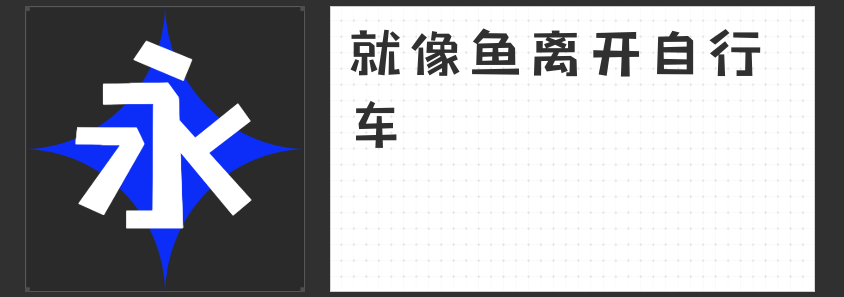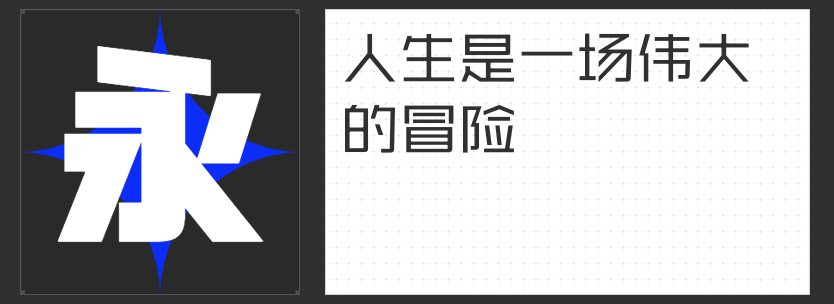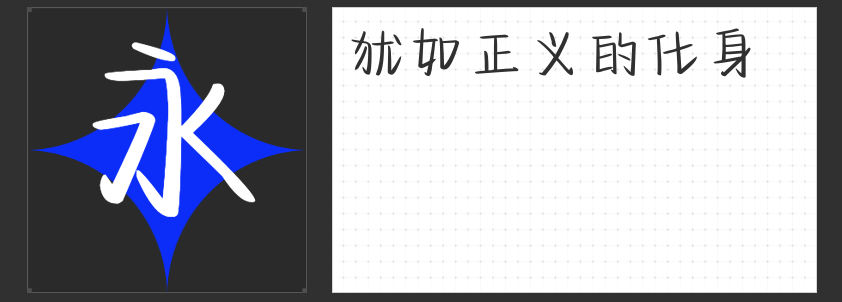
电商直通车不够醒目?这四款字体帮你提高效果
在电商设计中,字体选择至关重要,它不仅影响着整体视觉效果,还能准确传达品牌形象和产品特点。本文将为您推荐四款适用于电商直通车设计的字体。
1.高手字斋东京体
高手字斋东京体以其独特的创意风格脱颖而出,非常适合用于电商海报、广告标题以及包装设计中。这款字体线条流畅,字形饱满,能够迅速吸引消费者的注意力。其简洁明快的风格不仅符合现代审美,还能有效提升品牌形象的时尚感。
2.励字可变志向黑简
励字可变志向黑简是一款黑体风格的字体,兼具稳重与灵动。通过融合圆体与黑体的特点,它在笔画拐角处增加了适当的外圆角,使字体在保持稳重大气的同时,增添了一丝灵动与活力。这款字体非常适合用于电商网站的标题、海报设计以及产品详情页中,能够突出产品特点,提升整体视觉效果。
字圈也字综艺弹幕体以其手写风格和个性十足的设计,深受电商设计师的喜爱。这款字体线条粗犷而不失优雅,非常适合用于电商直播、弹幕评论以及社交媒体宣传中。它能够迅速营造出轻松愉快的氛围,吸引消费者的注意力,提升互动效果。
4.字圈也字狂想黑
字圈也字狂想黑是一款充满力量感和现代感的黑体字体,其独特的字形设计和强烈的视觉冲击力使其成为电商设计中的不二之选。这款字体非常适合用于电商广告的标题、促销信息以及产品包装中,能够迅速传达出产品的卖点,激发消费者的购买欲望。
综上所述,这四款字体各具特色,能够满足电商直通车设计中不同的需求。通过巧妙运用这些字体,设计师能够创造出更具吸引力和影响力的电商广告,助力品牌实现销售增长。